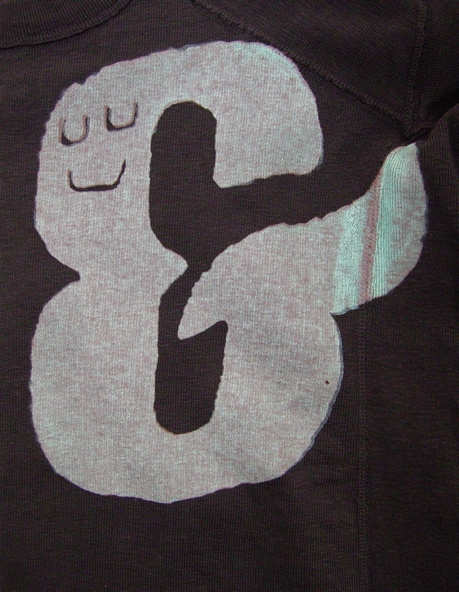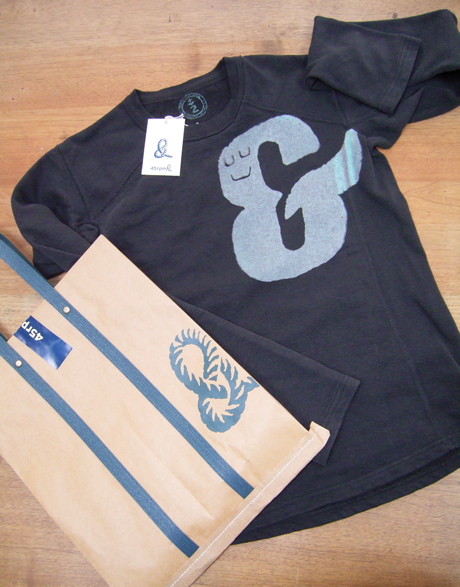
お店は、渋谷東急東横店2FのIMPRESSE(インプレッセ)です。
キツネがグータラ犬を飛び越す指輪
今日はクリスマス。みなさま特別な日をおすごしですか?
大切な人からのプレゼントは、今朝枕元にありましたか?
ワー羨ましい〜!きっと嬉しい笑顔がそこかしこ!
それなのに・・・・
我が家では、朝起きたときに私の枕元にいたのは、グースカ寝ている犬
だけでした・・・・。でもでも、そんな私にもなんと素敵なプレゼントがやって参りました。感動、感動、感動のリングです。
そしたら、ひゃ〜、なんともうひとつ入っていたのですよ。「グータラ犬を飛び越えるきつね」の文章が入ったリングが!
そうカリグラフィーをする人ならだれでも知っている文章ですよね: The quick brown fox jumps over the lazy dog. a〜zが全て入っている文章です。これを書けば全ての文字を練習できる便利なアルファベットセンテンスです。
それが指輪になってくれたなんて・・・・・・・。嬉しくて涙が出そう。
mikaさんの動物シリーズはとても好評ですが、アルファベットシリーズも素敵です。自分の好きな文章もきっと入れてもらえるかも!?
ふふふ。妄想はどんどんひろがるワ〜。
メリークリスマス! 素敵なクリスマスをお過ごし下さいね。
指輪とブレスレット
アクセサリーは、作家さんが作った限定もの、あまりたくさん出回っていないようなものが好きです。
画像の指輪とブレスレットは一緒に購入しまたが、全く違う場所で買ったペンダントも同じ作家さんだったので、きっと私はこのデザイナーさん(オランダ人だそうです)と波長が会うのかもしれません。
表ももちろん好きですが、私が気に入っているのは、この裏側! そう、アルファベットや数字が刻印されています。側面にも文字が入っているんです。いいでしょ~?
まるで江戸っ子の羽織みたい?表よりも裏地に凝っていて、チラリとしか見えないところなのにお金をかける・・・みたいな?
ブレスレットはじゃらじゃらして、たま〜に裏側の文字が見えて、何度も得した気分です。
指輪はごつくてサイズがちょっと大きいので、中指とか人差し指にしかできません。これを右手に付けてでは、カリグラフィーはちょっと無理かな〜。
首に巻く文字
このところ暖かい日が続いていますね。
でも、これから冬に向かうにつれて首元が寒くなってきます。そんな時には、文字を首に巻くのです!
紫色のスカーフは、何年か前のルネサンス展(か何か?)の時にミュージアムショップで思わず買ってしまったもの。なかなかこういうデザインがないため舞い上がって購入しましたが、実際身にまとう事はほとんどありません。
この展覧会に行った人はこのスカーフを目にしているので「あっ!買った人がいるんだ〜」と皆口を揃えて言います。それが恥ずかしくて、ついつい押し入れの 引き出しにしまったままでした。でも今年からはウォームビズで部屋の中も寒くなるでしょうから、ちょこっと暖かくなるためのグッズは必需品かも。
今年は思い切って使おうかな。
でもこうしてブログで紹介すると、きっと「あっ!ブログに載っていたやつだ〜」って言われてしまうかも・・・・。
皆様、これを目にした時は「あっ!あれだ!」と思っても口に出さず見守って下さいまし。
ちなみに、黒い方はご存知ロゼッタストーンのデザインのハンカチですが、どこで購入したかは忘れました。(印刷博物館だったかしら〜???)
アンパーサンドの顔
&のことをampersand(アンパーサンド)と呼びますが、先日可愛いカットソーを見つけました。
もともとアンーパーサンドの形は、EとTから出来ています。ラテン語のet(and)が由来です。ですから、eとtの組み合わせで、実にいろいろな形のアンパーサンドがあるのです。
この画像のアンパーサンドは、アンパーちゃんと呼ぼうと思います。とても嬉しそうな顔なので、ハッピーな気分になりますね〜。袋もちょっと素敵です。底の部分は紙テープで縫ってありました。
このメーカーは、45rpmという名前です。フォーティーファイブアールピーエムと読むそうです。(長っ!) お店は全国いろいろな所にあります。ネットで販売もしていますよ。
このカットソーは色違いで、茶色、グレー、白、ウスカーキがお店にはありました。身幅が少し狭くて、着るとカッコ良いです。